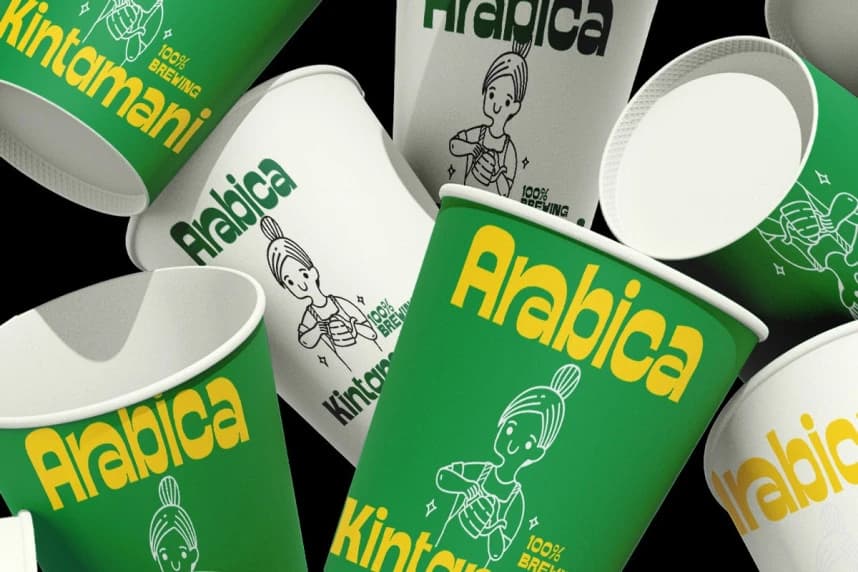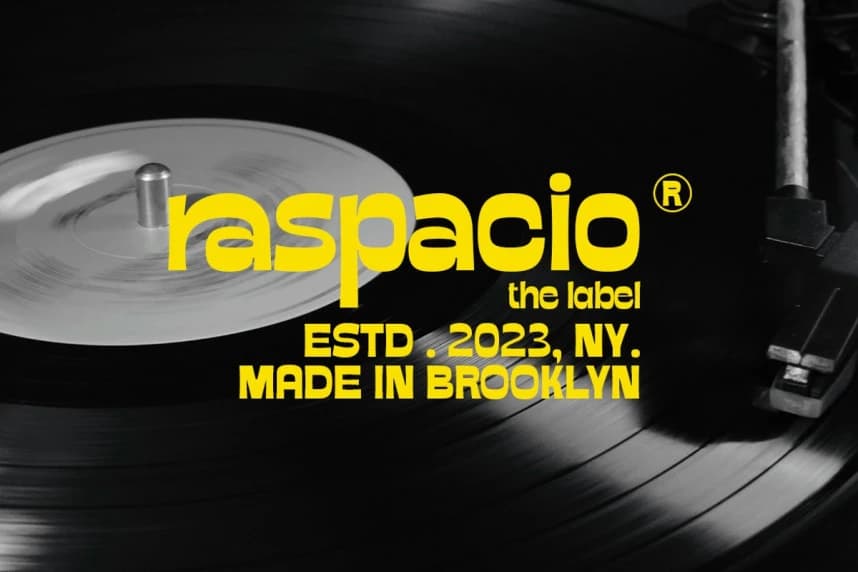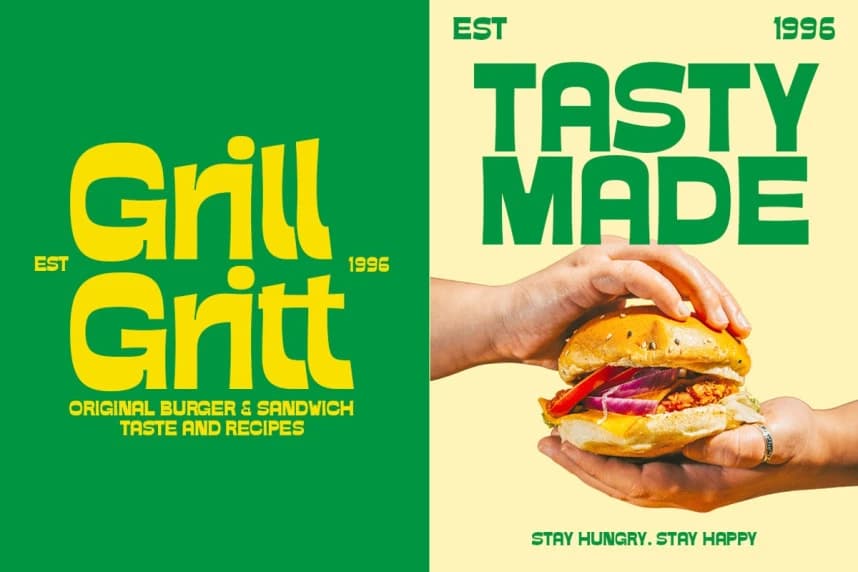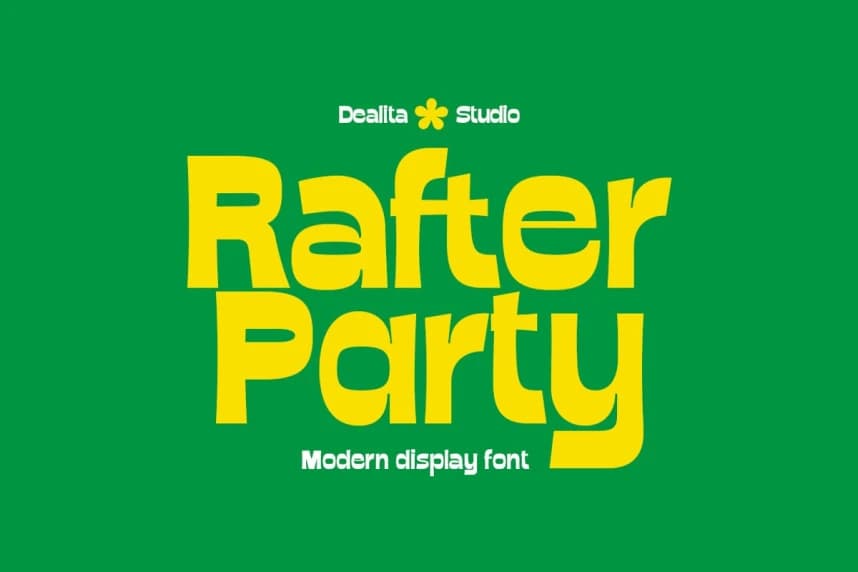
Rafter Party Font
Rafter Party Font - Modern kalın sans-serif ile oyuncu ink trap geometrisi buluşuyor. Rafter Party benzersiz ligatür dansı ve çarpıcı ink trap detayları sunar — partiye düşkün, fakat profesyonel kalmayı sürdüren bir markalaşma için mükemmeldir.
Rafter Party Font - Modern kalın sans-serif, eğlenceli mürekkep kapanması geometrisiyle buluşuyor. Rafter Party, benzersiz ligatür dansı + çarpıcı kapanma detayları sunar — profesyonel kalırken parti yapmayı seven bir marka kimliği için mükemmel.